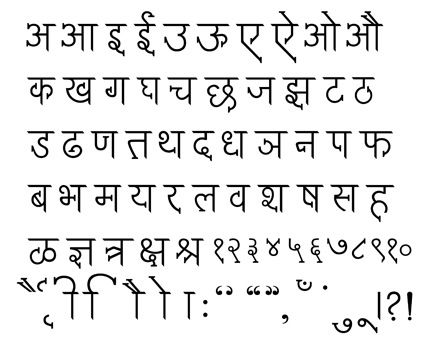
Попробуйте в графическом редакторе преобразовать вставленный текст в графику. Надпись превратится просто в набор пикселей, раскиданных по пространству холста. Точно также и с иероглифами, арабской вязью, для иностранцев — с нашей кириллицей, да со словами родного языка, написанными нечитабельным шрифтом. Неизвестные письмена на одежде превращаются всего лишь в украшение, прекрасное как формой. так и сокрытой в нем тайной. Это хорошо уловил режиссер Питер Гринуэй. В «Контракте рисовальщика», «Книгах Просперо» и особенно в «Интимном дневнике» он упивается разбросанными по экрану многоязыкими фразами.
Не случайно, дизайнеры любят использовать шрифты, стилизованные под чужой алфавит (например, заставка на «МузТВ»).
Необычные алфавиты — это кладезь возможностей сделать одежду необычной, яркой, запоминающейся. Мода может черпать и черпает в нем идеи. Особенно часто это было в 80-х, вероятно и через 20 лет по закону круговорота моды, они станут актуальны.
Амхарский. Азбука древней Эфиопии. Чем больше в мире становится людей с дредами, чем из большего числа плееров льется Lion in Zion Боба Марли — тем больше у него потенциала стать модным. Культура расты, как возвращения к африканским истокам вместе с примазавшимися белыми «вавилонянами» неминуемо сделает эти палочки с кружочками культовыми.
Арабская вязь. Культура, отрицавшая рисунок, возвела калиграфию в абсолют. Грех не использовать эти надписи тем более при нынешнем интересе к Востоку и исламскому миру в частности.
Деванагари. Индийский алфавит, закорючки. «подвешенные» к горизонтальной палочке. Индийский шрифт ужекосвенно вошел в моду на излете 90-х, когда дизайнеры украшали одежду картинками с многорукими божками. Этот же шрифт обыгрывается в последнем клипе Эминема, хотя и явно по ошибке.
В мире становится все больше успешных индийцев и возможно надписи на деванагари еще войдут в моду.
Иврит. Надписи на иврите были модными в 80-е. Самая знаменитая — на балахоне Боя Джорджа
Кириллица и глаголица. Если мы хотим преуспеть, нам нужно не переходить на латиницу, а сохранять и даже продвигать вовне кириллицу. Но это не единственный вариант. У нас ведь есть еще и другая азбука, более древняя глаголица! Мой совет русским дизайнерам, желающим использовать славянские этнические мотивы: присмотритесь к глаголице. Очень красивый шрифт. А главное, если иврит или индийские письмена кто-то опознает, этот отмерший алфавит будет выглядеть по меньшей мере.
Часто над японцами и китайцами иронизируют из-за их пристрастия к громким лейблам. Осмелюсь предположить: дело не столько в престиже. Для японца Chanel — такие же чуждие непонятные закорючки, как и для нас их хирагана и катакана. Народы, воспитанные на иероглифическом письме, ценят в лейблах не только значение, но и в не меньшей степени красоту шрифта и логотипа. Как хорошо было бы и европейцам уметь видеть Красоту в самых простых вещах.